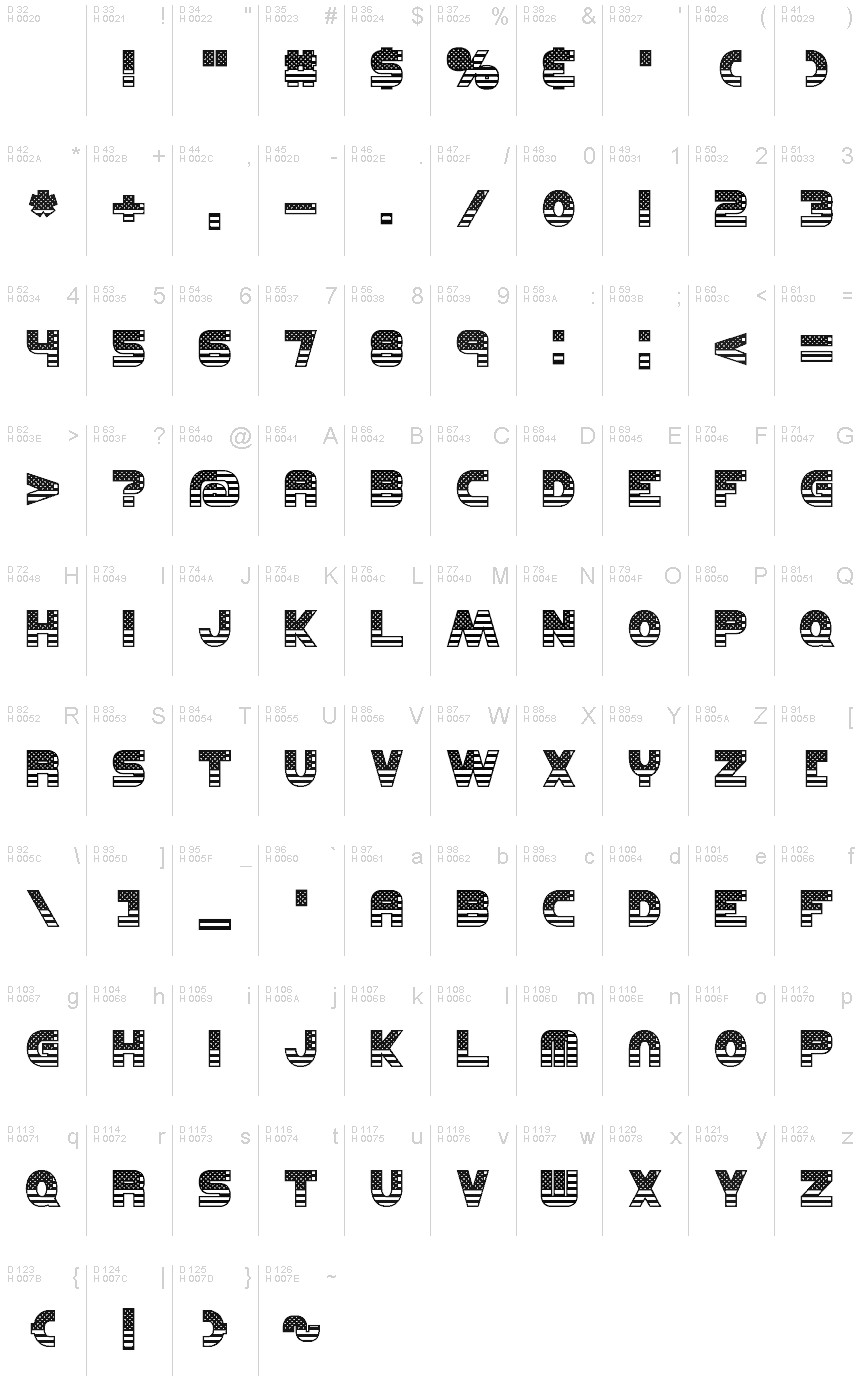
UNITED BRK, stworzony przez ÆNIGMA FONTS, to krój typu display, który przykuwa uwagę dzięki swojej bardzo wyrazistej grubości i szerokiej formie. Jego dekoracyjny styl wyróżnia się misternym wzorem wypełniającym każdy znak, co nadaje mu unikalną teksturę – zarówno intrygującą wizualnie, jak i zapadającą w pamięć. Estetyka UNITED BRK jest odważna i stanowcza, co czyni go idealnym wyborem do projektów wymagających silnego oddziaływania wizualnego.
Unikalny design UNITED BRK sprawia, że jest to doskonały wybór do kreatywnych zadań, takich jak plakaty, branding, kampanie reklamowe oraz wszelkie media, w których potrzeba mocnego akcentu. Dekoracyjny charakter tego kroju sprzyja artystycznym kompozycjom, w których typografia nie służy tylko do czytania, ale jest również dziełem sztuki.
Dzięki solidnej konstrukcji i rozłożystej formie, UNITED BRK oferuje nieskończone możliwości projektantom, którzy chcą nadać swoim pracom charakteru i polotu. Niezależnie od tego, czy użyjesz go w nagłówkach, czy jako centralny element grafiki, ten krój wyróżnia się umiejętnością łączenia estetyki z funkcjonalnym designem typograficznym.